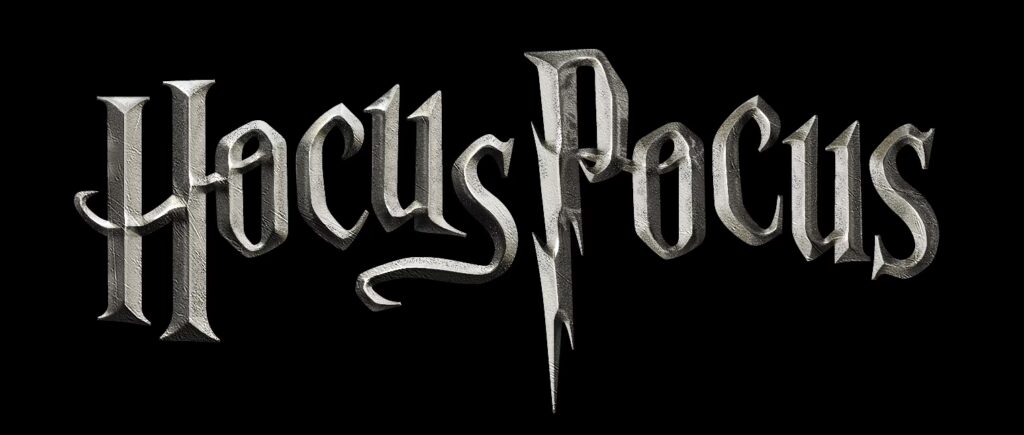
Nogle gange kræver et kreativt projekt bare et lille strejf af ekstra magi. Uanset om du designer invitationer til en temafest, laver digitale kunstværker, skaber indhold til sociale medier, eller endda tilføjer titler og tekst til dine fotografier, kan den rigtige skrifttype gøre en enorm forskel. En font er mere end bare bogstaver; den sætter stemningen, vækker følelser og kan transportere beskueren til en anden verden. Og hvis den verden er fuld af troldmænd, hekse og fortryllelser, så har du brug for en særlig type skrifttype.
Harry Potters verden har en unik visuel identitet, som mange ønsker at efterligne i deres egne projekter. Heldigvis behøver du ikke at kaste en dyb fortryllelse over din pengepung for at finde skrifttyper, der emulerer denne stil. Vi har samlet en liste over top gratis (for personlig brug) Harry Potter-inspirerede skrifttyper, som vi kunne finde. Fra elegante og fortryllende til skriblede og krøllede – disse skrifttyper vil løfte dit design mere, end hvis du kastede Wingardium Leviosa.
Hvorfor vælge en tematisk skrifttype?
Valget af skrifttype er et afgørende designelement. Ligesom et fotografi kan formidle en stemning gennem lys, farver og komposition, kan en skrifttype formidle tema, tone og personlighed. En elegant, skrøbelig font signalerer noget andet end en fed, robust font. Når du arbejder med et specifikt tema som Harry Potter, hjælper en tematisk skrifttype med øjeblikkeligt at etablere den ønskede atmosfære. Den genkendelige stil kan vække associationer hos modtageren og gøre dit budskab eller design mere effektfuldt. For fotografer, der måske laver albums, online gallerier eller marketingmateriale, kan brugen af en tematisk font på titler eller vandmærker tilføje et personligt og stemningsfuldt præg.
En verden af magiske skrifttyper
Her dykker vi ned i de specifikke skrifttyper, vi har fundet, og ser på, hvad der gør dem unikke, og hvordan du potentielt kan bruge dem i dine kreative bestræbelser. Husk altid at tjekke den specifikke licens for hver font, især hvis du planlægger at bruge den til kommercielle formål.
De elegante og klassiske stilarter
Nogle af de mest populære Harry Potter-inspirerede skrifttyper efterligner den stil, der ses i filmplakaterne og bogomslagene – ofte med et elegant, næsten middelalderligt eller gotisk præg, men stadig læseligt. Disse er perfekte til titler og overskrifter.
1. Wizard World: Denne font er et stærkt udgangspunkt for mange, der søger en klassisk Harry Potter-følelse. Den er elegant, læselig og ideel til overskrifter og sektionstitler. Downloaden inkluderer varianter med flere udsmykninger (flourishes) samt en mere forenklet version, som du kan blande ind for en mindre prangende stil. Hvis du har brug for en ret traditionel Harry Potter-font, er dette et godt sted at starte. Den har den velkendte, lidt spidse og fortryllende karakter, der straks leder tankerne hen på troldmandsskolen.
7. Parry Hotter: Måske den mest traditionelle af de Harry Potter-lignende fonter på vores liste. Parry Hotter er udgivet som shareware til alles fornøjelse. Den efterligner HP filmplakat-fonten utroligt godt og har meget at byde på. Vi anbefaler dog at bruge den primært til overskrifter og titler. Når denne font bruges over flere linjer, sætninger og afsnit, kan den blive utrolig svær at læse. Dens styrke ligger i dens umiddelbare genkendelighed og evne til at skabe et stærkt visuelt fokuspunkt.
8. Magic School One: Som navnet antyder, er denne font stærkt inspireret af temaet 'magisk skole'. Magic School-pakken er faktisk ikke bare én font, men to. Magic School One giver dig en mere elegant og middelalderlig skriftstil. Denne stil er ofte forbundet med gamle bøger, ruller og officielle dokumenter i fantasy-verdener, hvilket passer perfekt til stemningen på Hogwarts. Den er formel, men stadig med et strejf af det mystiske.
De finurlige og håndskrevne vibes
Ikke alle magiske skrifttyper behøver at være stive og formelle. Nogle har en mere personlig, håndskrevet eller endda lidt kaotisk følelse, der kan tilføje karakter og charme til dit design.
2. Romance Fatal Prima: Dit projekt behøver måske ikke noget, der specifikt er fuld af Harry Potter-magi, men i stedet ønsker du kun, at det skal fremkalde følelsen af troldmandsverdenen. Romance Fatal Prima kunne være det, du leder efter. Med en håndskrevet fornemmelse og lidt uærbødig og finurlig kerning og sporing er denne font ikke dit typiske valg. Tilgængelig gratis til personlig brug, men med kommerciel licens, har du et komplet sæt af tegn til at udføre al den magi, du har brug for. Dens uregelmæssigheder giver den et autentisk, næsten dagbogsagtigt udseende, der kunne passe godt til mere intime eller personlige projekter.
5. I Love a Ginger: Måske vores favoritfont på listen simpelthen på grund af navnet. I Love a Ginger er dejlig og værd at forelske sig i i sin egen ret. Ligesom Hermione og Ron eller Harry og Ginny passer nogle ting bare sammen. Og denne fonts tegn og glyffer er ikke anderledes. De vil krydre dine designs, tilføje finurlighed og en håndskrevet fornemmelse, ud over at give hele projektet lidt varme. Bare ved at se på denne varme og indbydende font ønsker vi, at vi var krøllet sammen i Vindelhuset med vores yndlingsfamilie af rødhårede. Denne font udstråler hygge og personlighed og er fantastisk til designs, der skal føles indbydende og venlige.
9. Kingthings Willowless: Kingthings Willowless er både smuk og svær at udtale. Dekoreret med stjerner, hvirvler og udsmykninger, der helt sikkert vil bringe glæde til dine seere, er Kingthings Willowless simpelthen en smuk font. Igen, denne begynder at se rodet ud, når den bruges over meget plads, så hold dit arbejde kort og præcist, og du vil have dit publikum fortryllet. Dens detaljerede udsmykninger gør den til et kunstværk i sig selv, bedst egnet til meget korte tekster eller initialer.